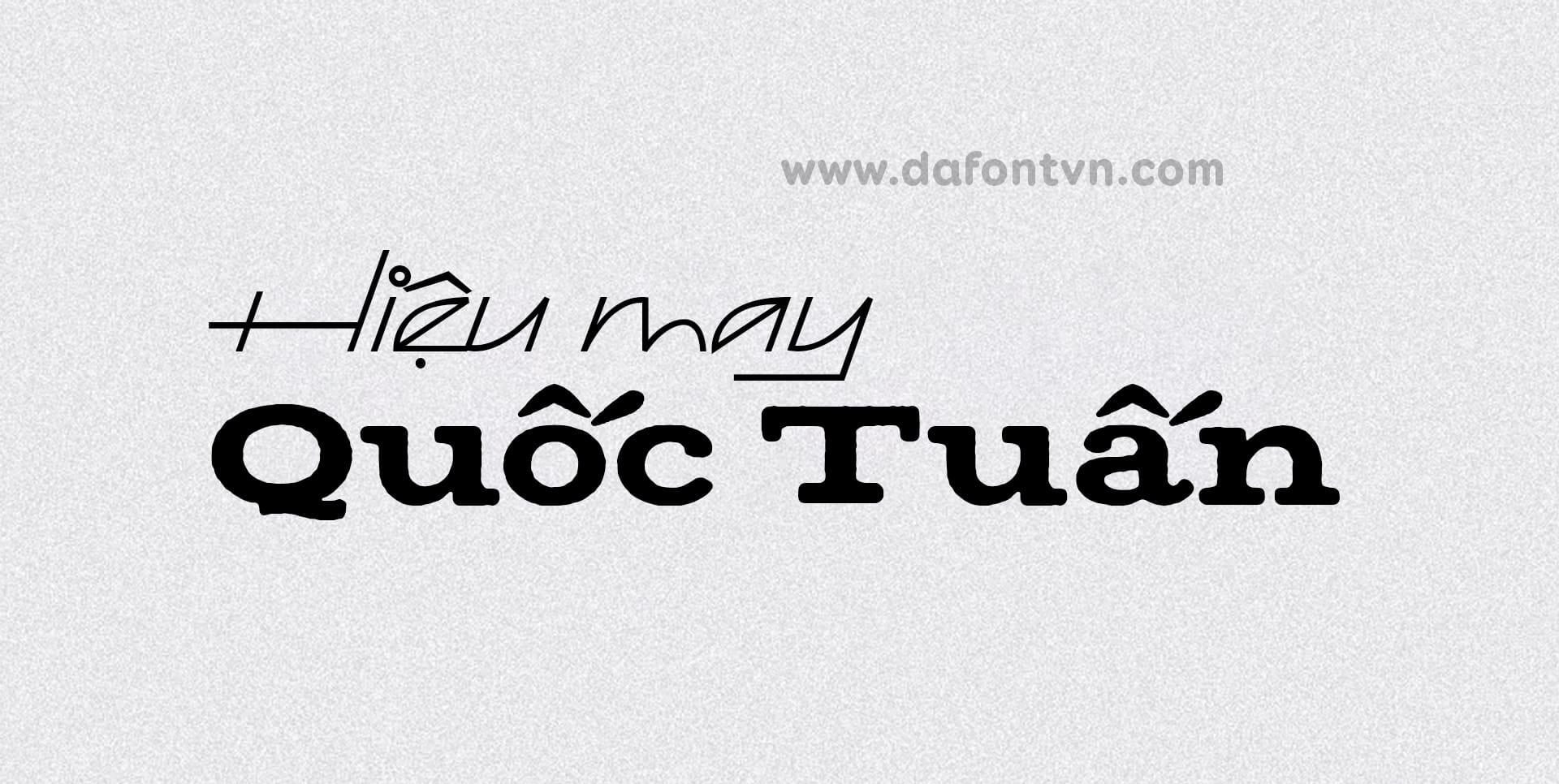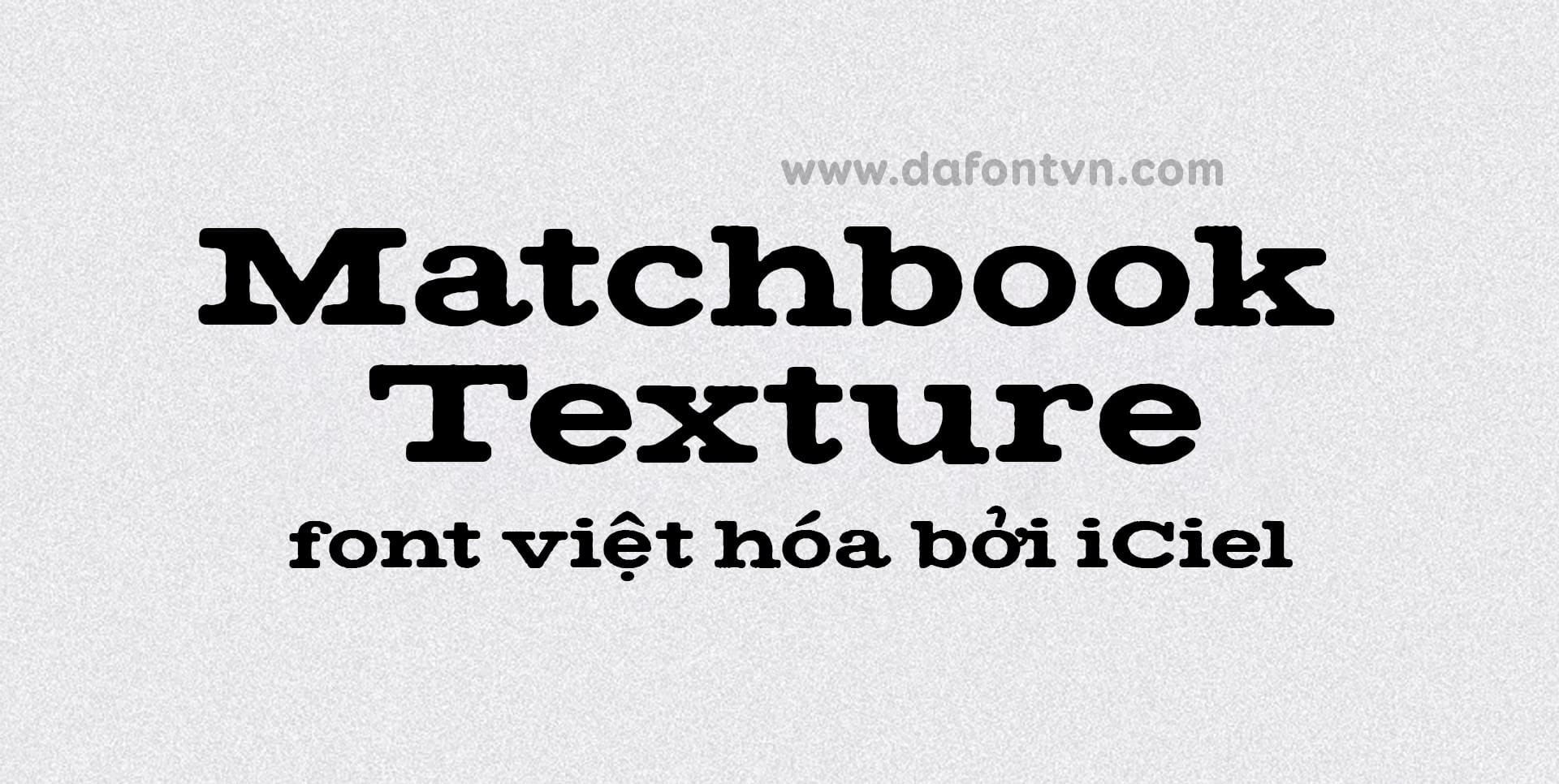
iCielBC Matchbook Texture Việt hóa nằm trong bộ font Hồi ức Sài Gòn được Việt hóa bởi iCiel.
Matchbook Texture là bản phát hành kiểu chữ đầu tiên của Simon Walker, phát triển từ các chữ được vẽ cho các tiêu đề phụ trong các phần thiết kế của riêng của tác giả. Với dạng chữ mở rộng và các serifs tròn của nó tạo ra một thiết kế đặc trưng và độc đáo trong các tiêu đề.
Đây là một trong những font chữ cổ điển ấn tượng với những đường nét retro vẫn luôn được ưa chuộng trong ngành thiết kế. Trong các ấn phẩm banner, poster hay các sản phẩm nhỏ lẻ như thiếp mời tiệc cưới, v.v thì font chữ cổ điển vẫn đang được sử dụng rộng rãi.